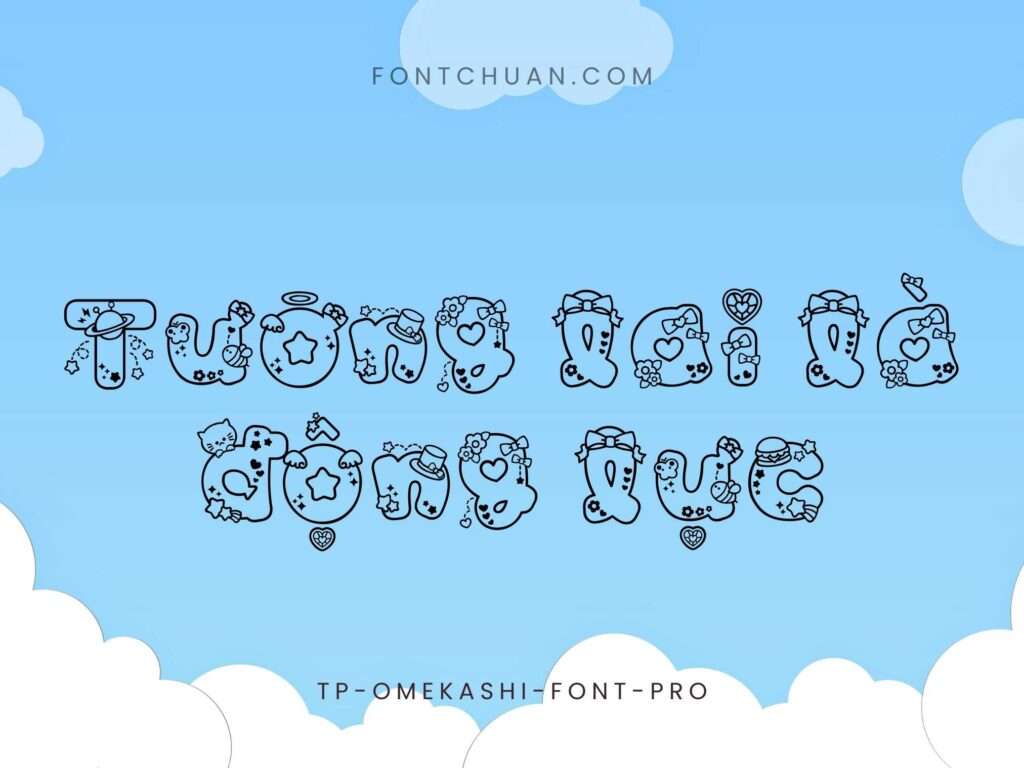
Font TP Omekashi Pro Việt Hóa
Tác giả Font: Norio Kanisawa
Omekashi Font Pro là một font chữ trang trí độc đáo, được thiết kế bởi Nozomi Seto và phát hành bởi SetoFont. Font này nổi bật với các ký tự được trang trí bằng các yếu tố dễ thương như hoa, sao và nơ, tạo nên sự vui tươi và sinh động cho các dự án thiết kế. Font đã được Việt hóa để hỗ trợ tiếng Việt bởi Tuỳn Pucca, giúp người dùng Việt Nam dễ dàng sử dụng trong các dự án sáng tạo. Font này được sưu tầm và chia sẻ bởi thành viên của Font Chuẩn, đáp ứng nhu cầu sử dụng đa dạng trong cộng đồng thiết kế.
Đặc điểm thiết kế của Omekashi Font Pro bao gồm các chữ cái được trang trí tỉ mỉ, tạo cảm giác vui nhộn và thân thiện. Font này phù hợp cho các ứng dụng như thiết kế thiệp mời, bìa sách thiếu nhi, poster sự kiện và các dự án sáng tạo khác. Các ngành nghề phù hợp bao gồm quảng cáo, nghệ thuật và thiết kế đồ họa.